日付アレンジを真似するときのコツ
「かわいい日付アレンジを試してみたいけれど、いざ書くとバランスが悪くなってしまう…」
そんなお悩みはありませんか?今回は、バランスを取りにくいデザインを例に、うまく書くコツ をご紹介します。
アイデアブックを参考にするのは難しい?
ただ実際に書いてみると「なんだか整わない…」と感じることも?
例① 「月・日・曜日」で構成されたデザイン
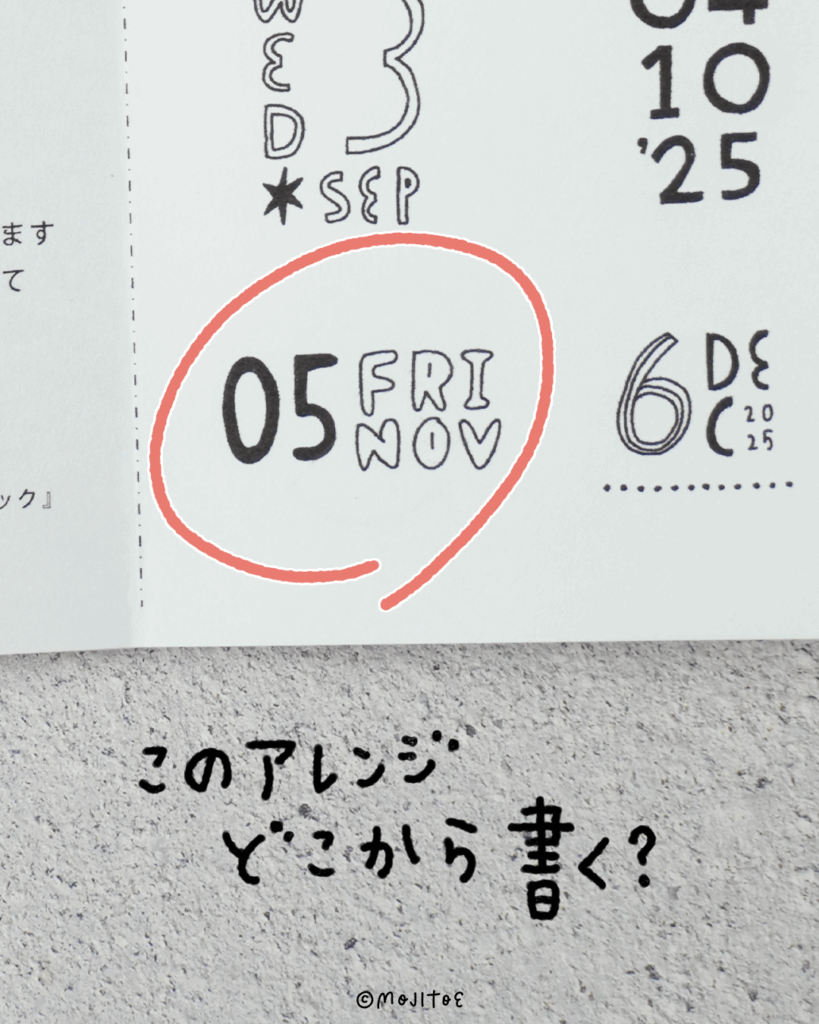
見本は「11月5日金曜日」。
要素を分解すると「月・日・曜日」の3パーツに分かれています。
これを「10月28日火曜日」にアレンジしてみましょう。
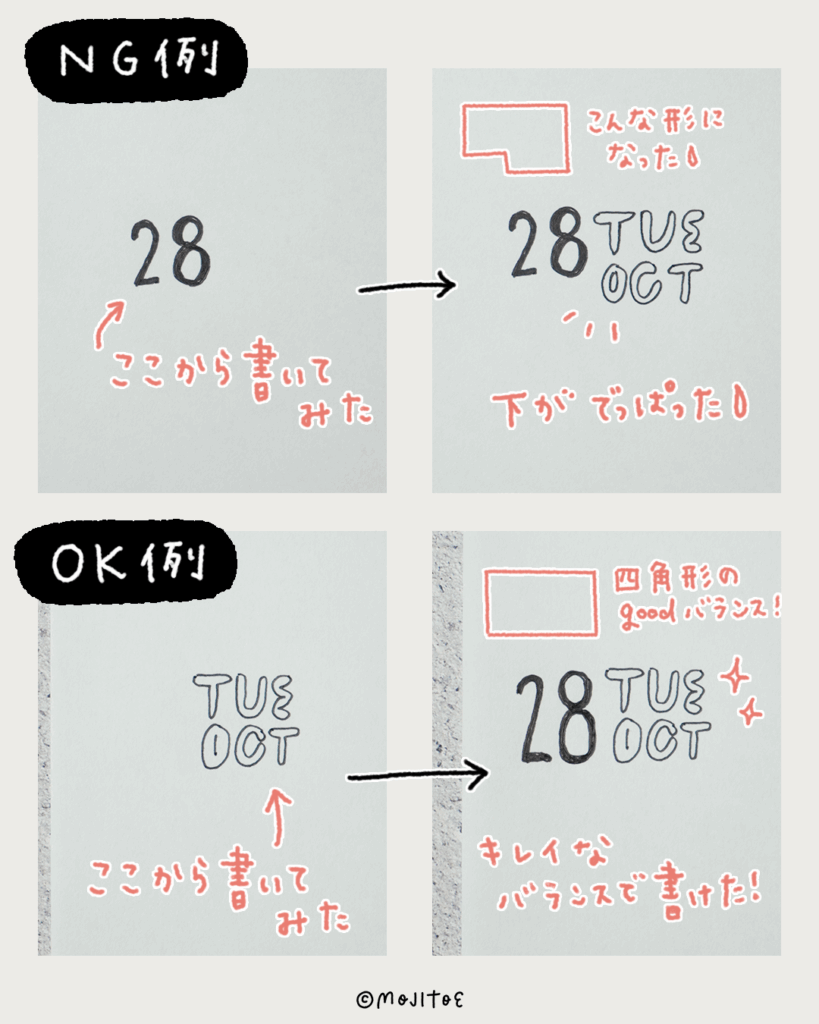
❌ NG例
「日」→「曜日・月」の順に書いた結果、「月」の部分が下にはみ出してアンバランスに。
⭕ OK例
「曜日・月」→「日」の順に書くと、全体が四角形に収まってGOODなバランスになりました。
つまり、書き始める順番を少し工夫するだけで整いやすくなる のです。
例② 「年・月・日・曜日」で構成されたデザイン
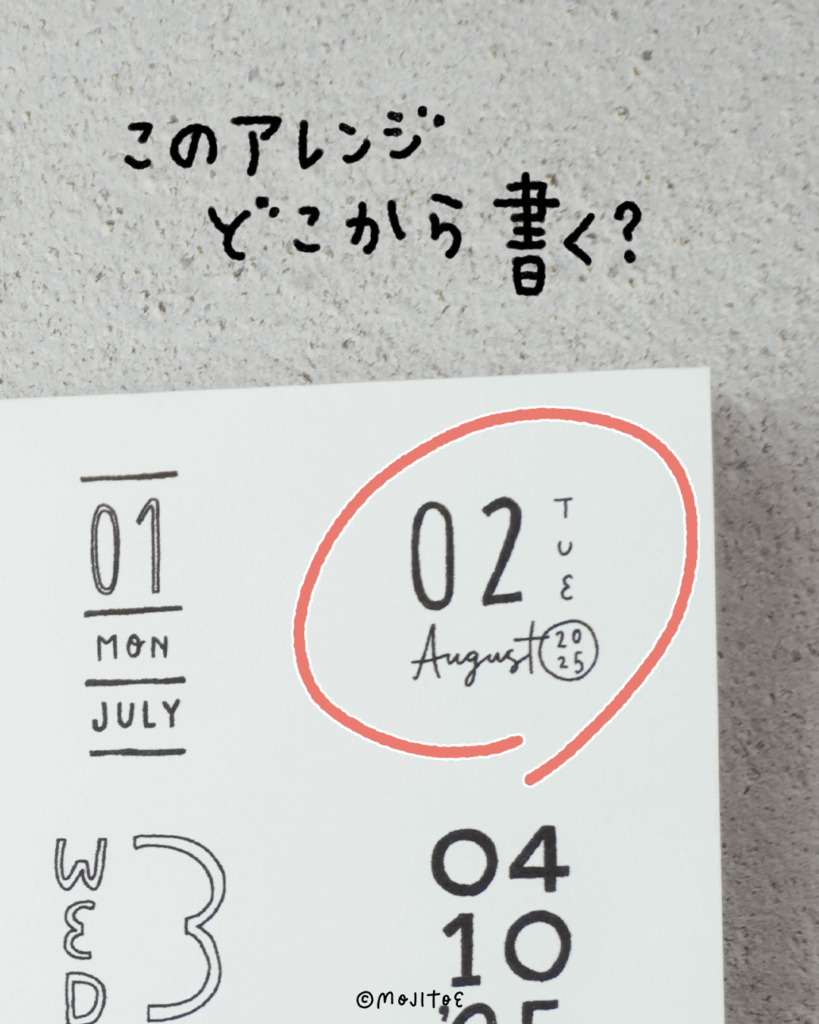
次は「2025年8月2日火曜日」のデザインを参考に、「2025年10月15日水曜日」を書いてみます。
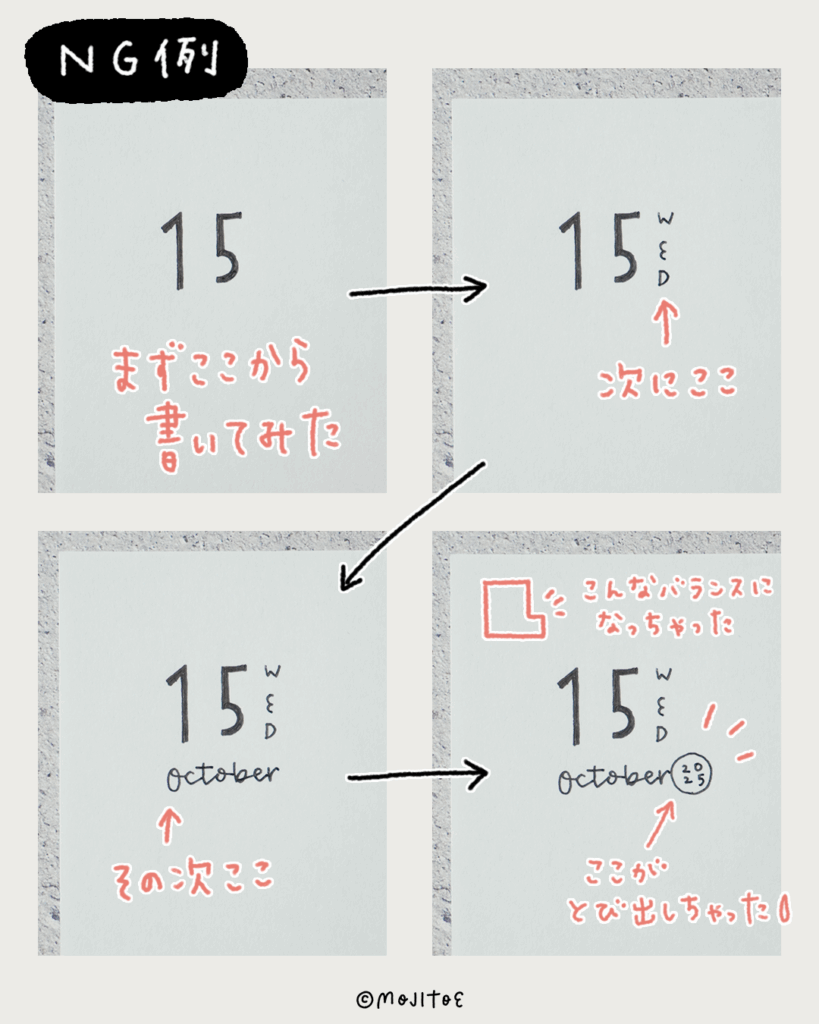
❌ NG例
まず「日」を大きく、その右に小さく「WED」。
次に「October」を下に書き、最後に「2025」を加えました。
すると「October」が長いため、「2025」が右にはみ出してしまいました。
⭕ OK例
最初に「月・年」から書き、そこに収まるように上段に「日・曜日」を配置。
すると、全体がきれいに四角形に収まりました。
月名を省略せず書くデザインは、月によって文字数が変わるので事前に考慮しておくのがポイント です。
ハンドレタリングでよくあるケース
- センター揃えのデザイン → 中央から書き始める
- 丸型デザイン → 最初から完璧な丸を狙わず、少しずつ整えていく
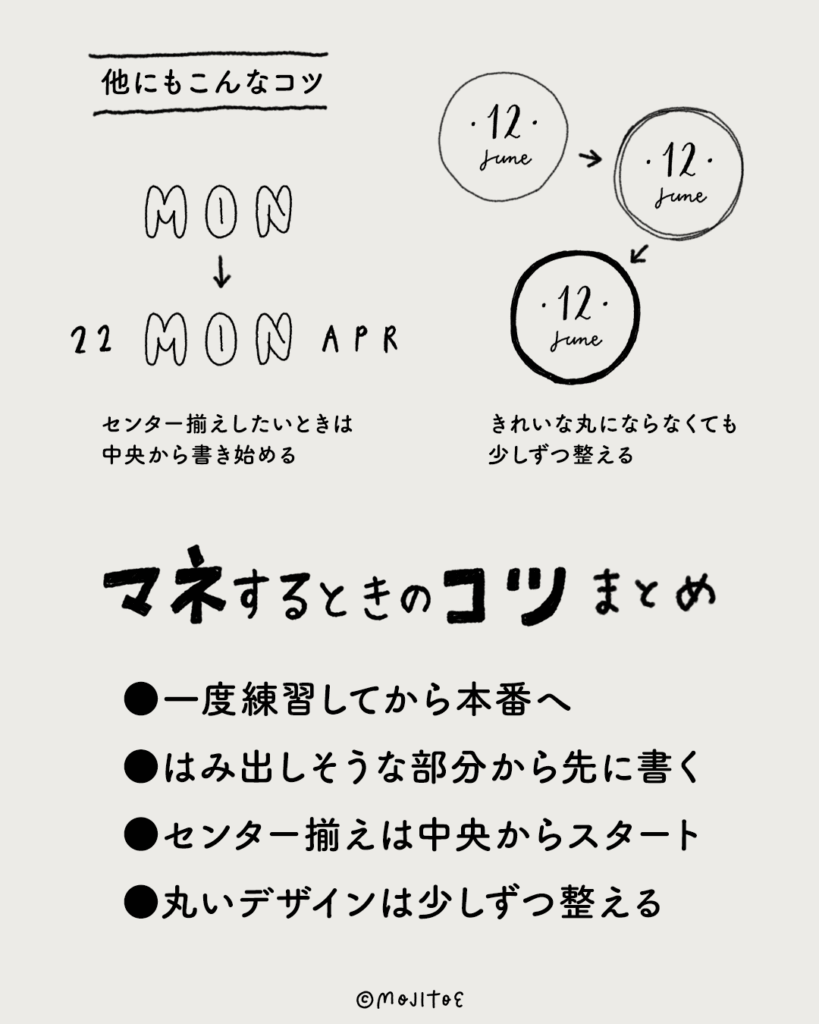
まとめ:真似するときのちょっとしたコツ
- 一度練習してから本番へ
- はみ出しそうな部分から先に書く
- センター揃えは中央からスタート
- 丸いデザインは少しずつ整える
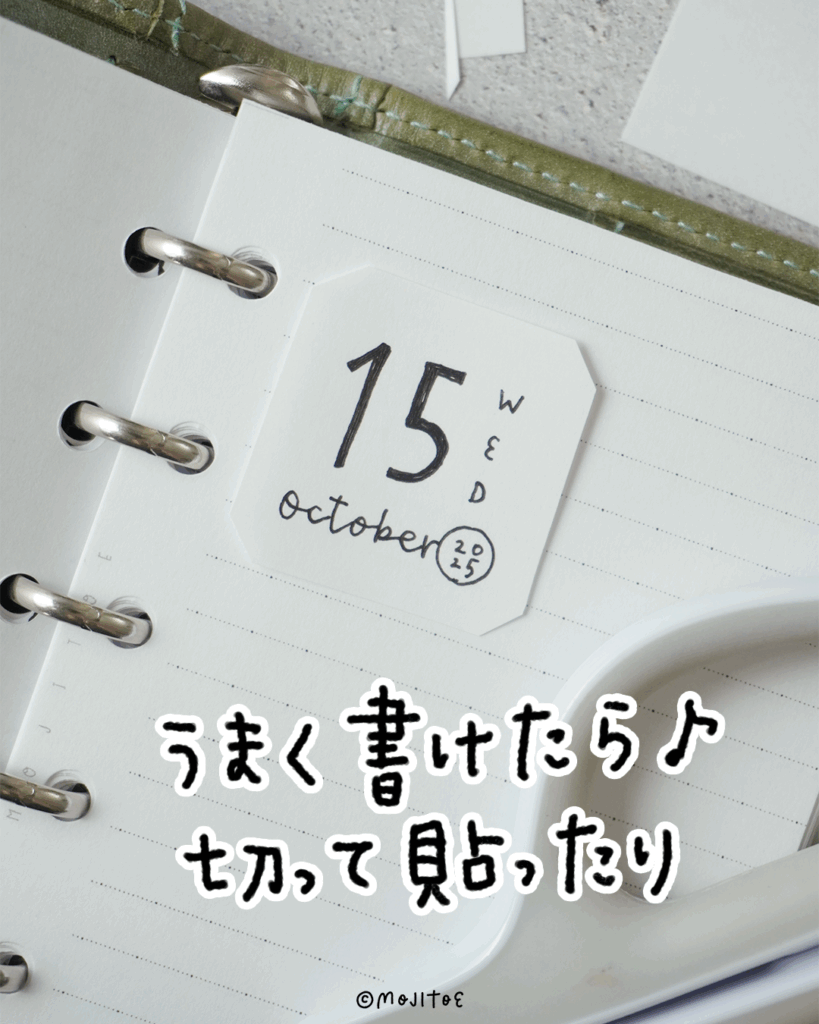
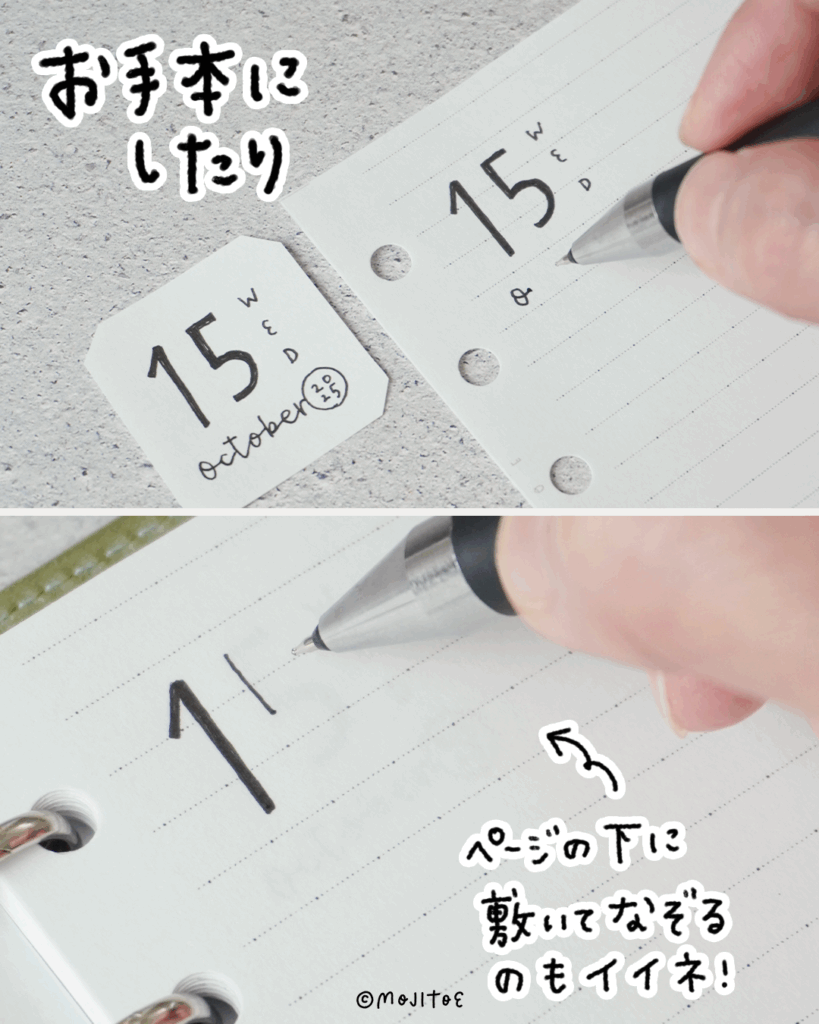
うまく書けたら紙を切って貼ったり、お手本にしてなぞったりするのもおすすめです。
今回は、日付アレンジをきれいに真似するためのコツをご紹介しました。
ちょっとした工夫で、バランスよくかわいく仕上がります。
ぜひ気軽に試して、楽しい手書きアレンジを楽しんでくださいね♪